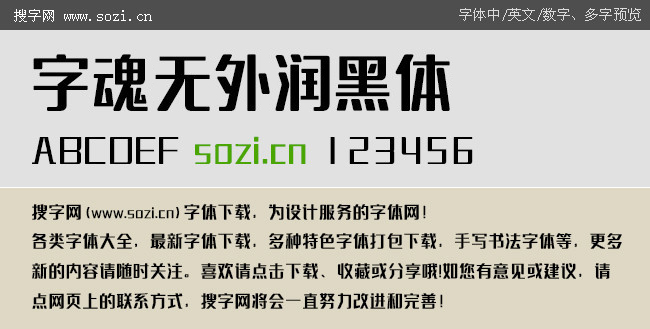
字魂5號-無外潤黑體
搜字網(wǎng)提供一款字魂5號-無外潤黑體中文字體下載,該字體包含6763個中文、字母、 符號和數(shù)字,具有現(xiàn)代、簡約、時尚、國際化 的風(fēng)格,可以滿足您設(shè)計上的各種需求,該字體主要用于新媒體、電商、廣告、海報企宣、媒體、社交 等場景。